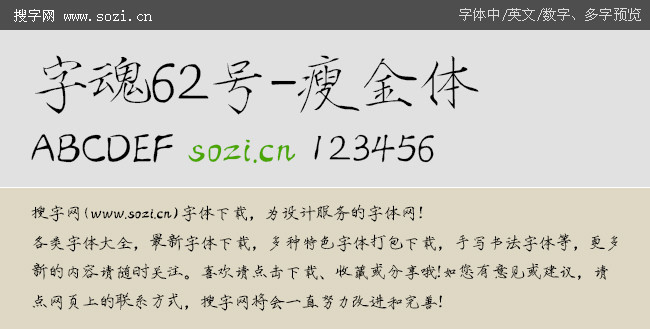
字魂62號-瘦金體
搜字網(wǎng)提供一款字魂62號-瘦金體中文字體下載,該字體是一款硬筆手寫字體,該字體包含6763個中文、字母、 符號和數(shù)字,具有現(xiàn)代、簡約、優(yōu)雅、浪漫 的風(fēng)格,可以滿足您設(shè)計上的各種需求,該字體主要用于印刷品、屏顯、印章、企業(yè)店鋪、電商、H5 等場景。